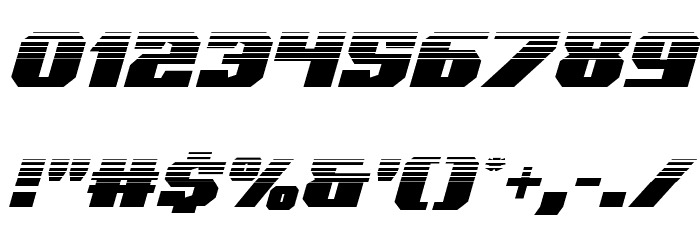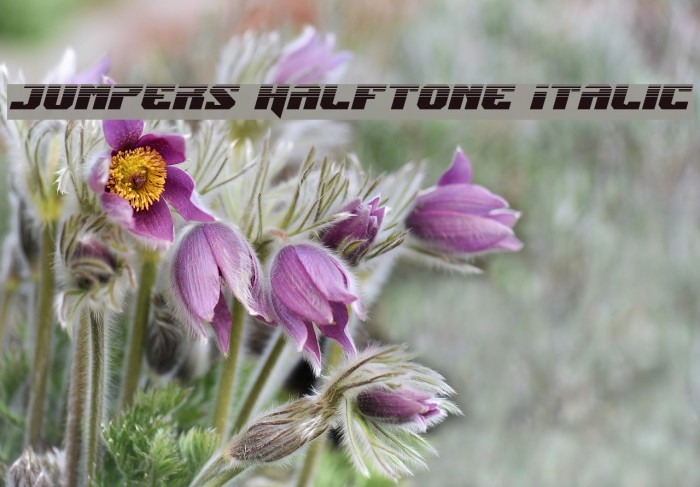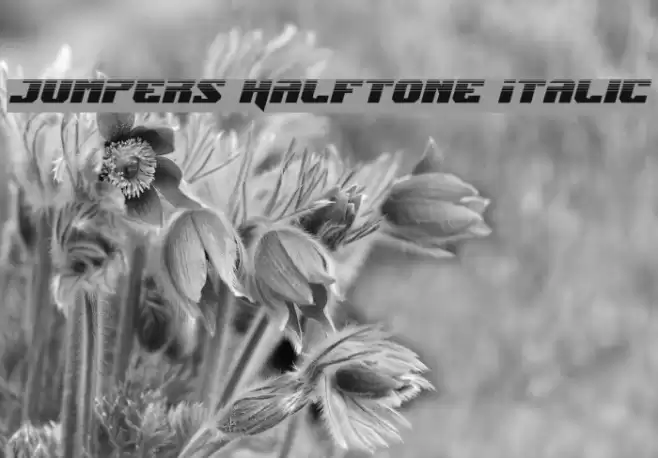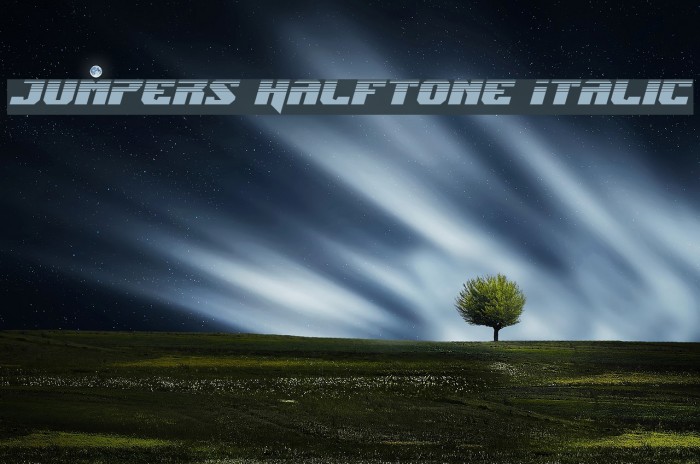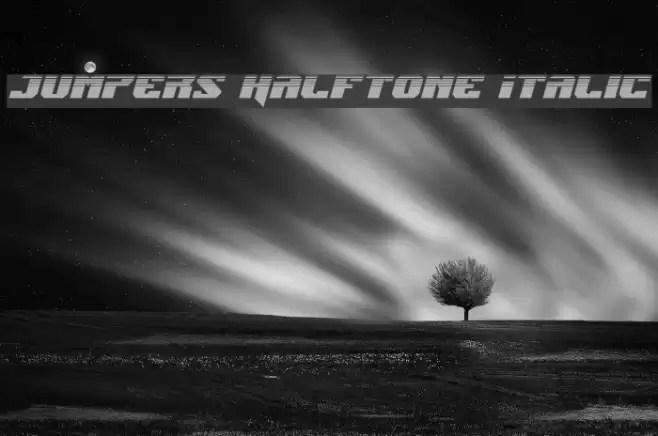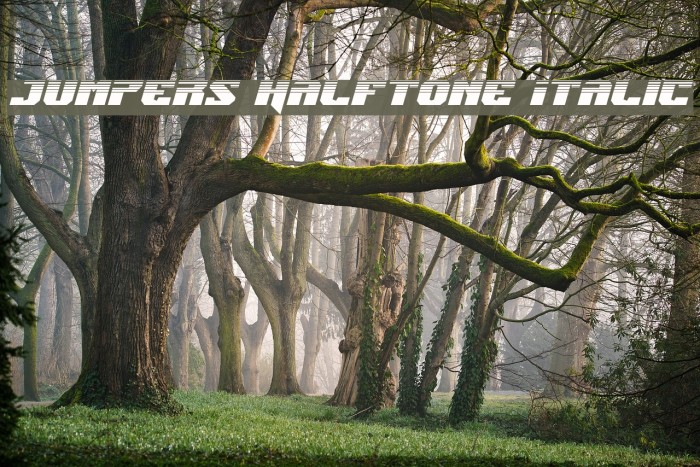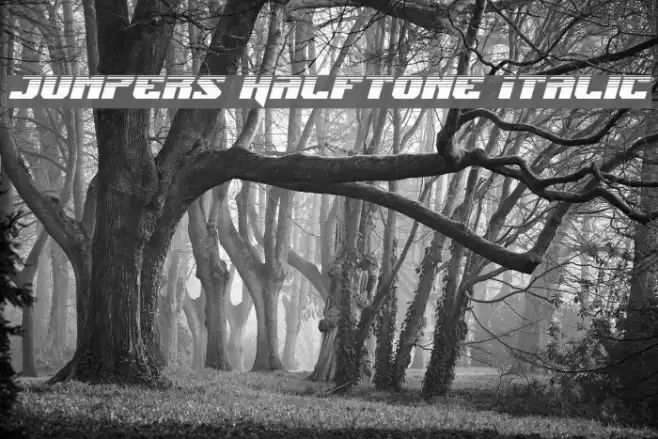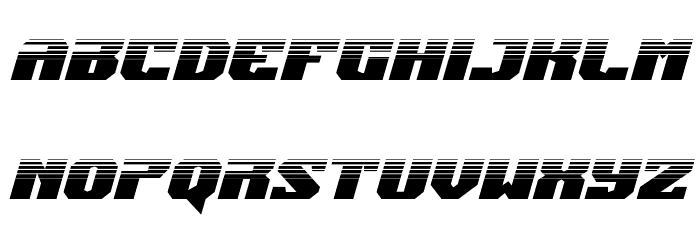
Jumpers Halftone Italic Font
| Stil general | Futuristic, Dynamic |
| Proiecte propuse | Ideal for sci-fi themed posters, video game titles, modern branding, and dynamic logo designs. |